タトゥーの中でも人気を博すレタリングタトゥー。その名の通り「文字のタトゥー」ですが、このフォントの選定には時間も労力もかかるため、容易ではありません。
それは、永久的に体に残るタトゥーだからこそ、美しく仕上げるべく、雰囲気や内容、フォントサイズ、フォントの太さなど、さまざまな側面を考慮する必要があるからです。
そこで今回は、レタリングタトゥーの「フォント選びのハウツー」と「フォント作成のハウツー」を紹介します!楽しみながらタトゥーフォントを作成してみてください。
レタリングタトゥーとは?
レタリングタトゥーとは、文字と数字を使用したタトゥーのこと。レタリングはタトゥーのデザインとして、非常に人気があります。
レタリングタトゥーは名前や日付、感傷的な言葉やフレーズなど、メッセージを大胆かつダイレクトに表すことができるのも特徴です。バランスよく仕上げることで、それらはメッセージ性だけではなくデザインとしても美しさを醸しだします。
では、レタリングタトゥーをデザインするときには、一体どのようなことを考慮しないといけないのでしょうか。以下ではレタリングタトゥーの基礎知識について解説します。
スペルと文法
正しいスペルと文法は、インクを入れる際に最も必要なことだといえるでしょう。永久的に残るレタリングタトゥーを入れるにあたって、スペルミスや間違った文法ほど残念なことはありません。
そのため、手遅れになる前にチェック、ダブルチェック、トリプルチェックを行い、および第三者にも確認してもらうとよいでしょう。ネイティブの知り合いがいる場合は、ネイティブにもチェックしてもらうことをおススメします。
メッセージ
タトゥーの内容も非常に重要です。タトゥーを入れるにあたって、多くの人は他の人にあなたのデザインを見てもらい、彼らにそれを理解してもらうことを望んでいるはずです。愛する人の名前であれ、有名な引用文であれ、自分の体に何を刻むのか、理性的によく考えて決めましょう。
他の言語でレタリングタトゥーを入れる場合は、必ずその言語のネイティブスピーカーに内容やスペルを確認してもらってください。Googleに頼るだけではいけません。文脈やニュアンスがどれだけ重要か分からないからです。
また、より高度な表現にしたい場合は、象形文字や数字を入れることもできます。ただし、意味があなたの意図に合っているかどうかは、常に確認しましょう。
タトゥーフォント
正しいタトゥーフォントの選定も、タトゥーデザインのプロセスにおいて非常に重要な要素です。また、タトゥーをパーソナライズすることができるのも楽しいポイントであると言えます。
フォントを選ぶときは、メッセージの内容や長さ、そしてレタリングタトゥーで引き出したいムードを考慮してください。いくらそのフォントが好きだとしても、そのフォントとメッセージの相性がよいとは限りません。
間違ったフォントを選択してしまえば、全体の雰囲気が台無しになってしまう可能性があります。例えば、手書き風のフォントでは上手くいったと思っても、それが皮膚に適用したときにも紙面やスクリーン上と同じようになるとは限りません。フォントとインクの相性を確認するために、タトゥーアーティストとフォントについて話し合うことも重要です。
サイズ
文字の大きさを考えることも大切です。メッセージの内容、選んだフォントでの見え方、体のどこにタトゥーを入れるかによって、大きさを調節する必要があります。
大きすぎたり小さすぎたりすると、読みやすさや体とのバランスに影響を与え、デザインから遠ざかってしまう可能性があります。これは、タトゥーアーティストと話し合うべき、もう一つの重要なプロセスです。
紙の上ではすべてが完璧に見えるかもしれませんが、皮膚へのタトゥーは多くの変数を含み、期待していたものとは異なる結果になる可能性があることを念頭に入れておきましょう。
タトゥーフォント BEST40
それでは、カテゴリ別に集められた素晴らしいタトゥーフォントのコレクションをご覧ください。
クールなタトゥーフォント
壮大で上品なデザインのフォントです。通常の伝統的なタトゥーフォント以外のものを探しているならこれらのフォントがオススメ!これらのフォントは、シンプルでクリーン、そして現代的で、長い引用文や短い引用文にも最適です。
- Bebas Neue Thin
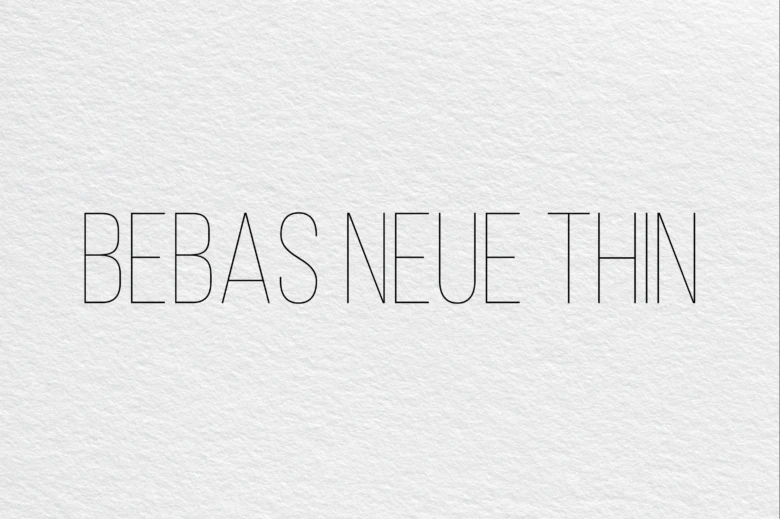
- Hope Sans Thin Italic
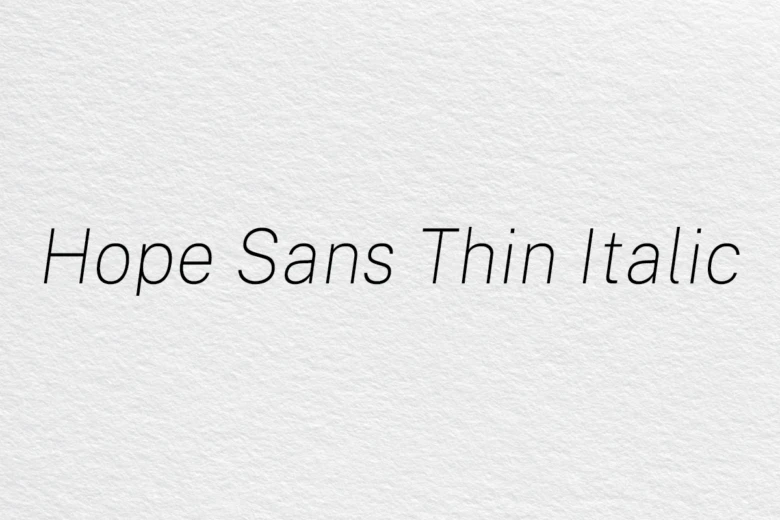
- New Garden Light
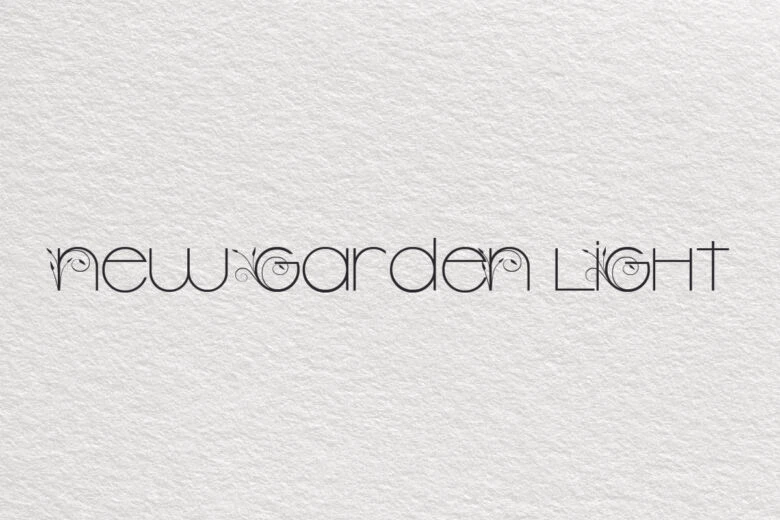
- Stela UT
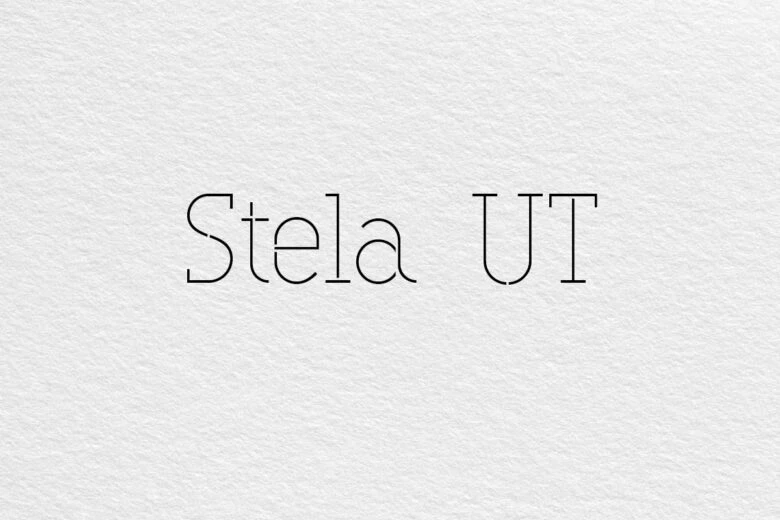
- Avellino
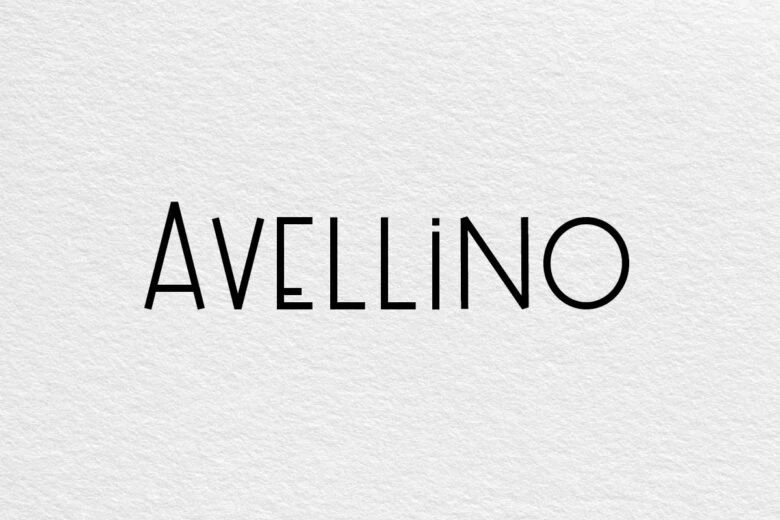
- Beyond Sky
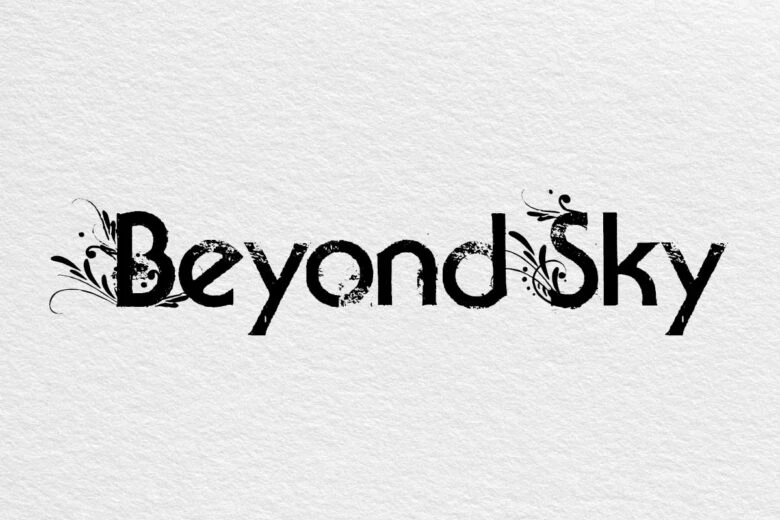
- Rose Tattoo
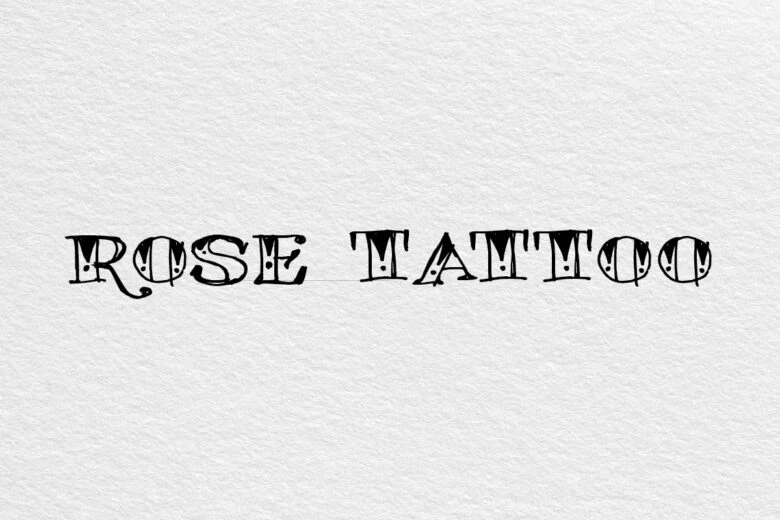
- Ginga
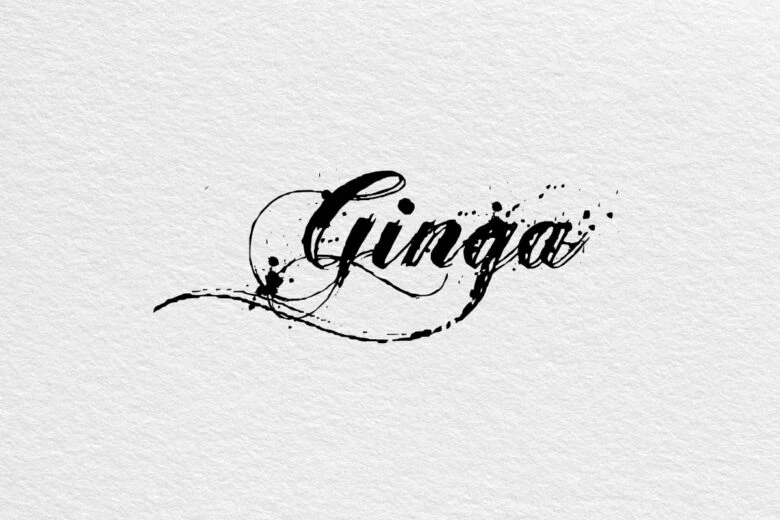
- Cutive Mono
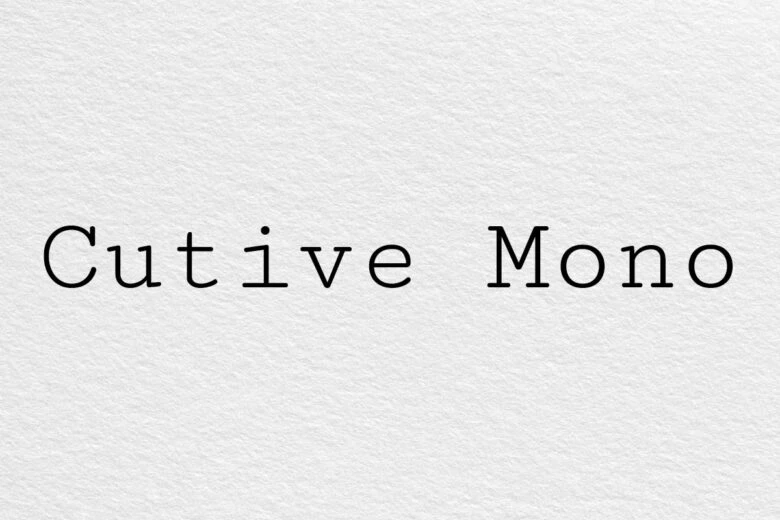
- Barclay Outline
伝統的なタトゥーフォント
こちらはタトゥーのレタリングに広く親しまれているフォントです。筆記体やカリグラフィースタイルの手書きのような筆跡を表現できるフォントで、流れるような優雅な読み心地が特徴です。名前や日付などの短いテキストに使用することをオススメします。
- Old English Std
- Bernhardt Standard Std
- Lucida Blackletter
- Edwardian Script
- Wedding Text Std
- Old Fashion Script Std
- Sverige Script Decorated
- Pennybridge 1563
- Coneria Script Medium
- Angilla Tattoo
キュートなタトゥーフォント
より繊細で女性的なタトゥーフォントを探している方には、こちらのコレクションがオススメです。これらのフォントは、キュートでソフトな見た目が印象的です。
- French Script
- Good Pro
- Lettering Delight
- Glastonbury Std
- Ringer Light
- Dove Love
- Perfograma
- Acryle Script
- Caneletter Sans
- Dawning of a New Day
ユニークなタトゥーフォント
もし、既成概念にとらわれないものを望むなら、このユニークなタトゥーフォントのリストをご覧ください。これらは典型的なフォントではありませんが、全体のデザインに何か特別な要素を加えることができる多数の特性を持っています。
- Victorian Inline Shaded Std
- Premier Shaded Std
- Farrier ICG Shaded
- Lombardic Capitals Std
- Killed DJ
- Do Not Exist
- Hedera ITC TT
- Cabaret Std
- Core Dodam
- Cineplex Std
タトゥーフォントのデザインアイデア
デザインを個性化する方法は無限にあります。決め手となるのは、好みとデザインの目的です。それでは、タトゥーフォントデザインのアイデアをご紹介します。
- ミニマルデザイン
ミニマルデザインとは、文字や画像を最小限に抑えた、極めてシンプルなデザインのことです。例えば、名前、日付、シンボルなどが含まれます。これらはクールタトゥーフォントカテゴリにある現代的なフォントと相性が抜群です。
- トラディショナルデザイン
トラディショナルデザインは、ミニマルデザインとはほぼ対極で、アニメーションやディテールを多用した大胆なデザインです。トラディショナルデザインでは、さまざまな色やシェーディング、アウトラインの異なるテクニックを使用することができます。トラディショナル・タトゥー・フォントにリストアップされているフォントのいずれかを使用することをオススメします。
- 絵と文字の組み合わせ
絵と文字の組み合わせのデザインは、デザインの目的や好みによって大きく異なります。画像のテーマに沿っていれば、どんなタトゥーフォントでも問題ないでしょう。
- フォントの組み合わせ
1つのデザインに2つの異なるフォントを組み合わせる人も少なくありません。この2つのフォントがうまく融合すると、とても魅力的なデザインになります。良いフォントの組み合わせについて詳しく知りたい場合は、「フォントペアリング完全ガイド」をご覧ください。
- アウトラインとシェーディング
文字のアウトラインの内側や外側に、模様や絵などのディテールを取り入れたデザインです。シンプルなシェーディングから、より複雑なパターンを各文字の中に入れることもできます。アウトラインやシェーディングが組み込まれたフォントの使用がベターです。